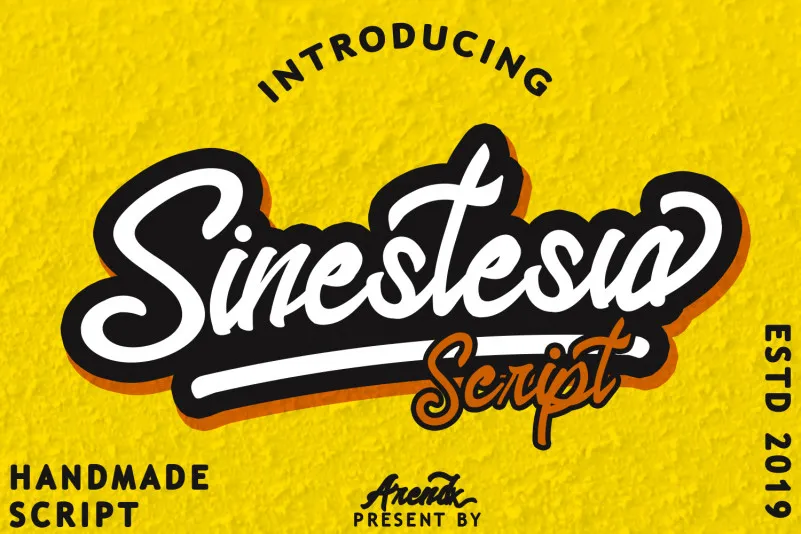
Sinestesia Script Font – Download Grátis
A Sinestesia Font é uma curiosa escolha para quem procura personalidade em suas criações digitais. Transformada de letra feita à mão, esta fonte única e com um encanto próprio se destaca por seu charme único e sua forma fluida, perfeita tanto para uso no design de logotipo ou marca palavra, quanto em identificação visual como selo, placas de parede, panfletos, cabeçalho, roupas e convites de casamento. Este projeto foi cuidadosamente desenvolvido pelo designer arendxstudio para oferecer um conjunto completo no formato OTF, TTF e WOFF, facilitando a integração do design no seu sistema. O mais interessante é que não é necessário qualquer programa especializado para usar esta fonte. Basta instalá-la de maneira tradicional como fazia normalmente em seu sistema. Sem dúvida alguma, ela vai adicionar uma dose única e autêntica ao seu trabalho de design.